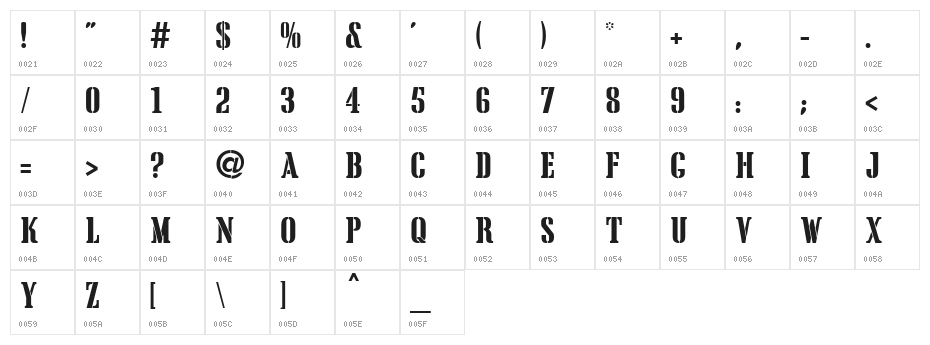
Crate Font
| Gesamtstil | Vintage |
| Vorgeschlagene Projekte | Ideal for use in posters, branding, headlines, and any design requiring a strong, authoritative typeface. |